Schöne Schriftarten für 2021
Schöne Schriftarten gesucht? Hier kommen Fonts, die im wahrsten Sinne des Wortes ausgezeichnet sind. Außerdem: die Lieblingsschriftarten von Designern, echte Schriften-Klassiker, kostenlose schöne Schriftarten und mehr.
Jeder empfindet Schriftarten anders oder entwickelt im Laufe der Zeit persönliche Vorlieben. Die einen setzen lieber auf schöne und bewährte Schriftarten, andere möchten ausschließlich angesagte Fonts nutzen. Für manche muss es sogar kostenlos sein. Wie dem auch sei: Für alle gibt es hier schöne Schriftarten – und zwar nach Kriterien sortiert.
Schöne Schriftarten – vom TDC ausgezeichnet
Wenn es nach den Experten aus New York geht, sind wohl dieses hier die schönsten Schriftarten. Der Type Directors Club zeichnet jedes Jahr besonders gelungene und schöne Schriftarten aus. 2020 konnten 15 Fonts das begehrte „Certificate of Typographic Excellence“ – so etwas wie der Oscar unter den Schriften – gewinnen. Diese Auswahl zeigt einige der Highlights aus dem aktuellen Typografie-Wettbewerb. Die komplette Liste aller Gewinner sowie die Sieger der Vorjahre kann man auf der Website vom TDC einsehen.
Eine Auswahl der vom TDC ausgezeichneten Schriftarten in 2020:
PF Marlet
Kessler
Prelude
Flecha
Schijn
Einige der vom TDC prämierten Schriftarten in 2019:
Rizado Script
Gliko Modern
Heldane
Kraken Slab
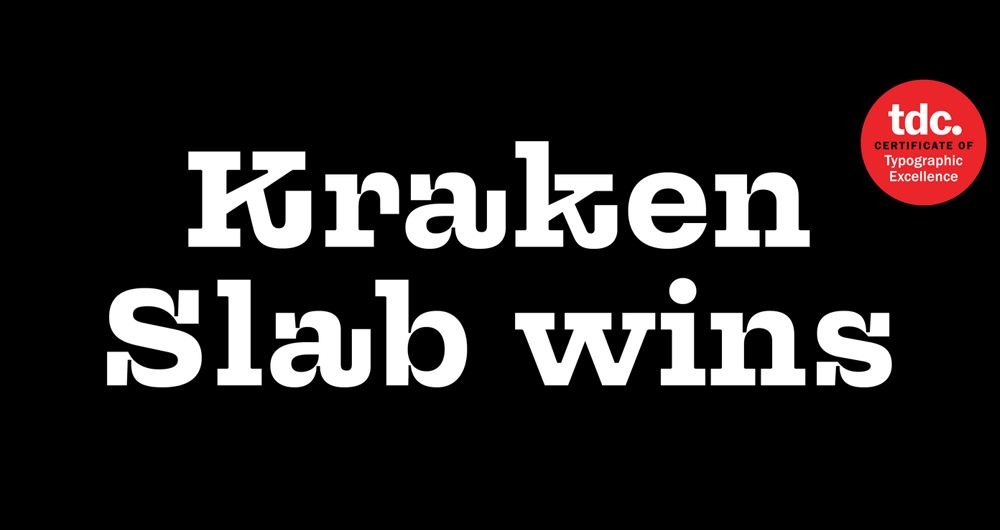
Faune
Sandwitch
Pyk
Hier kommt außerdem eine Auswahl der ausgezeichneten Schriftarten aus 2018:
Lamon
IBM Plex
Origen
Teddy
Harrison Serif Pro
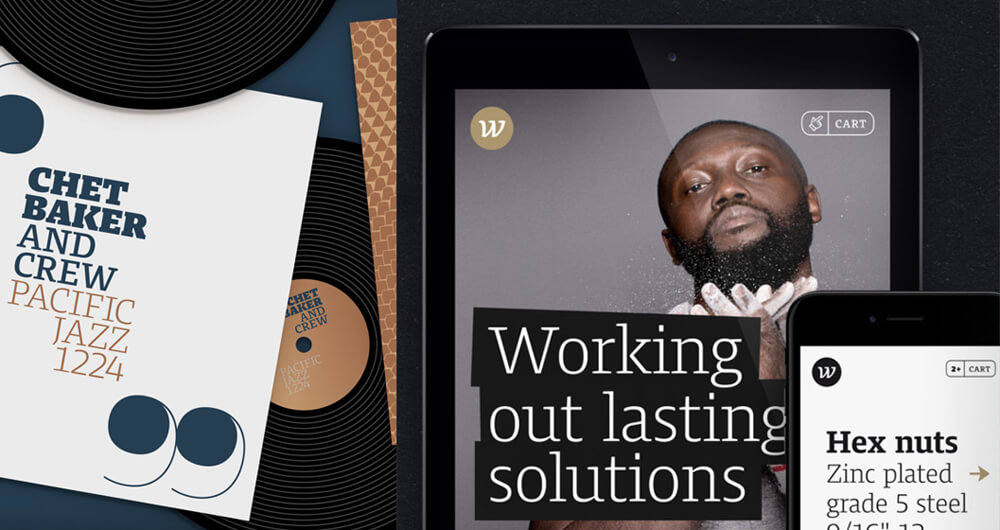
Guyot
Oi!
Lieblingsschriftarten von Designern: Schöne Schriften aus Sicht von Kreativen
Erkundigt man sich mal bei Designern nach schönen Schriftarten, so kommen dabei oft ungewöhnliche Empfehlungen bei heraus. Der Umstand kommt nicht von ungefähr, denn Kreative richten ihr Augenmerk häufig auf Details in der Typografie. Einige Designer fühlen sich von schönen Ligaturen angesprochen, andere ziehen Zierelemente vor und weitere Kreative bevorzugen lieber exakt ausgearbeitete Corporate Fonts. In den Lieblingsschriften von Designern und Typografen spiegelt sich zudem auch der Zeitgeist wider.
Den Lieblingsschriften von Designern hat der Schriftenanbieter Linotype eine eigene Serie in seinem Schriften-Magazin gewidmet. Dort verraten beispielsweise die Typografen bzw. Designer Felix Bonge, Mårten Thavenius, Arne Freytag, Brigitte Schuster, Anders Francker und Sarah Lazarevic, welches ihre Lieblingsschriftarten sind.
Auf der Seite „100besteschriften“ listet die Jury, bestehend aus den Designern Roger Black, Stephen Coles, Jan Middendorp, Veronika Elsner, Bertram Schmidt-Friderichs, Ralf Herrmann und Claudia Guminski ihre Favoriten unter den Schriften.
Die Schriftenseite „Typewolf“ hat außerdem 41 einflussreiche Designer nach ihren Lieblingsschriften gefragt. Das Ergebnis kann man hier (in Englisch) sehen.
Kosenlose schöne Schriftarten
Was sind kostenlose schöne Schriftarten? Diese Frage lässt sich nicht so einfach beantworten, denn es gibt keine festen Kriterien an denen man das ausmachen kann. Der eine mag lieber schwungvolle Schreibschriften und der andere verbindet mit kostenlosen Fonts dann doch eher komplette Schriftfamilien. Einem geschenkten Gaul schaut man bekanntlich nicht ins Maul und so freuen sich viele Nutzer über das, was sie kostenlos ergattern können. Verständlich – denn oft ist die Qualität sehr ordentlich. Studenten bieten ihre Studienarbeiten zum Herunterladen an und Typefoundries möchten ihre schönen Schriften durch GiveAways vermarkten.
Der versierte Typograf findet bei diesen kostenlosen und schönen Schriftarten sicherlich die eine oder andere Stelle innerhalb der Buchstaben, die einer Optimierung bedarf. Dieser Umstand ist vielleicht bei einem Preis von 0 Euro verschmerzbar, da sich Details im Nachhinein noch von Hand den eigenen Vorstellungen anpassen lassen.
Im Rahmen der sogenannten Free Goods of the Week* stellt die Kreativplattform Creative Market jede Woche neue Downloads vor, die man eine Woche lang kostenlos herunterladen darf. Darunter befinden sich dann auch meist ein oder zwei schöne Schriftarten. Auch durch eine intensive Suche auf Myfonts.com lassen sich kostenlose Einzelschnitte ausfindig machen. Sie werden häufig zur Einführung von neuen Schriftfamilien bereitgestellt und dienen der Vermarktung.
Zu den Schriftanbietern, die neben ihren Schriftfamilien auch immer gern hochwertige und schöne Free Fonts zum Downloaden anbieten, zählen die Kreativen von FontFabric – mit schönen Schriften wie Colus, ColorTube oder Mixa.
Auf Designer in Action stellen wir zudem regelmäßig neue Free Fonts vor. Vor allem sind das Schriften, die uns in diesem Jahr besonders aufgefallen sind sowie weitere Fonts, die für Designer in Action interessant sind. Ein Blick lohnt sich, da das Archiv regelmäßig um neue Fonts ergänzt wird. Wer selbst einen tollen Free Font entdeckt hat, kann uns dieses gern mitteilen. Wir freuen uns über jeden Tipp, der über das Kontaktformular eintrifft. Die ausgesuchten Free Fonts von Designer in Action gibt es hier.
Schriften-Anbieter, Typedesigner und Typefoundries